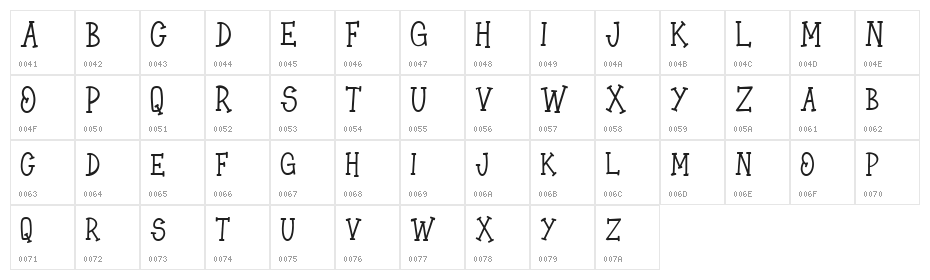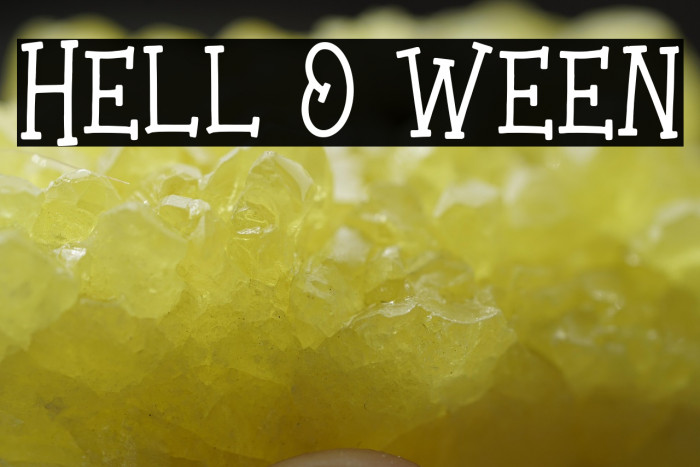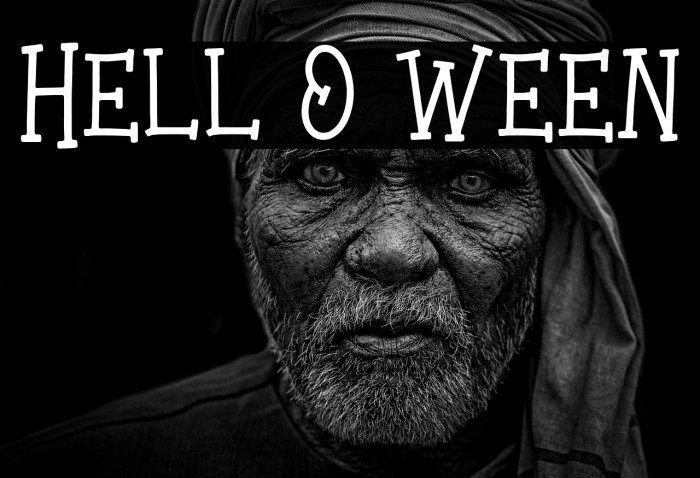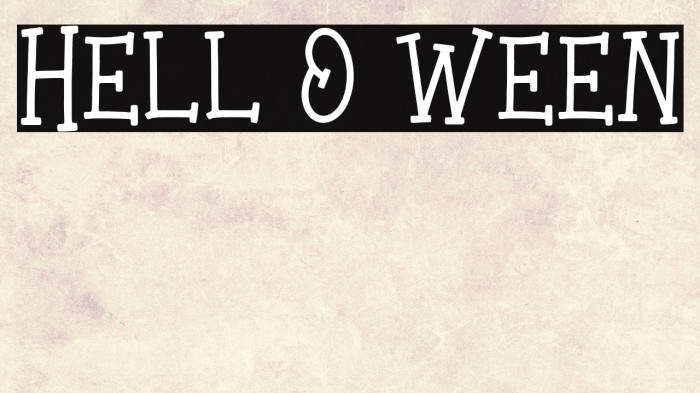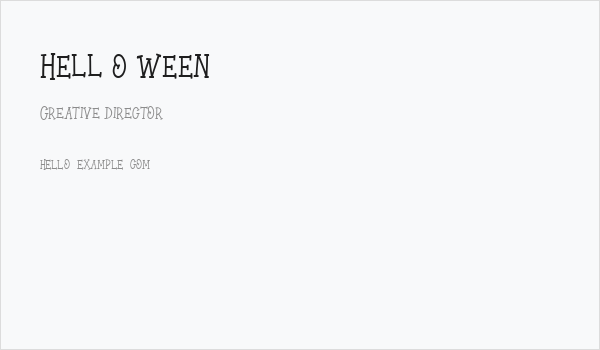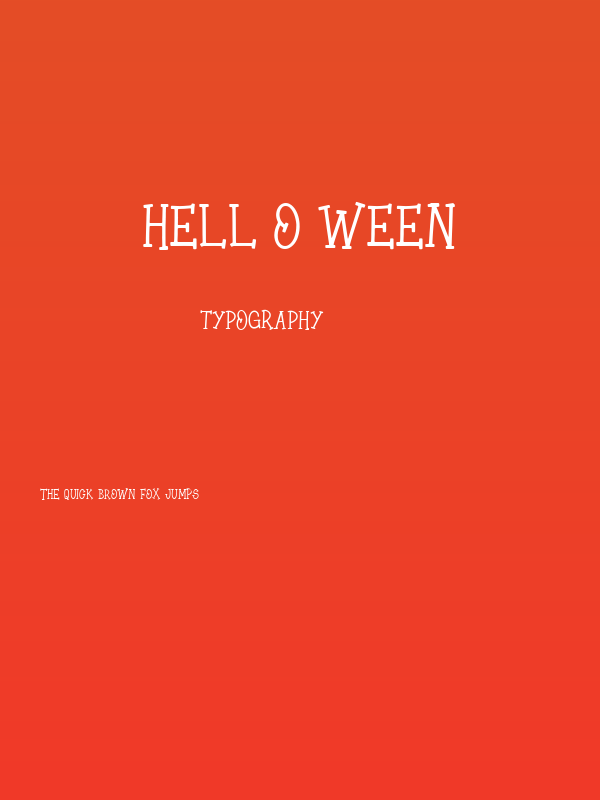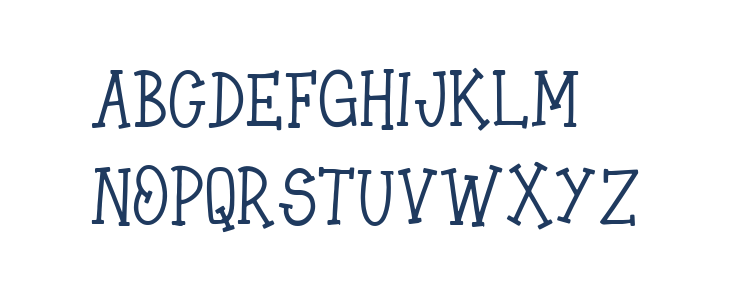
Hell o ween Font
| 用途 | Headlines, Logos, Invitations |
| おすすめプロジェクト | Ideal for Halloween-themed designs, children's books, party invitations, and playful branding. |